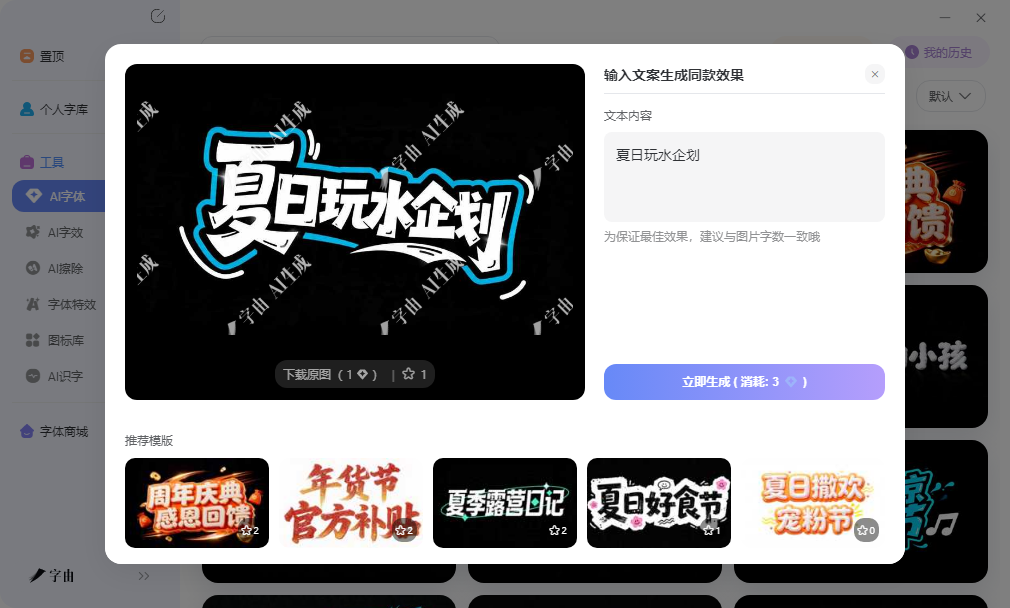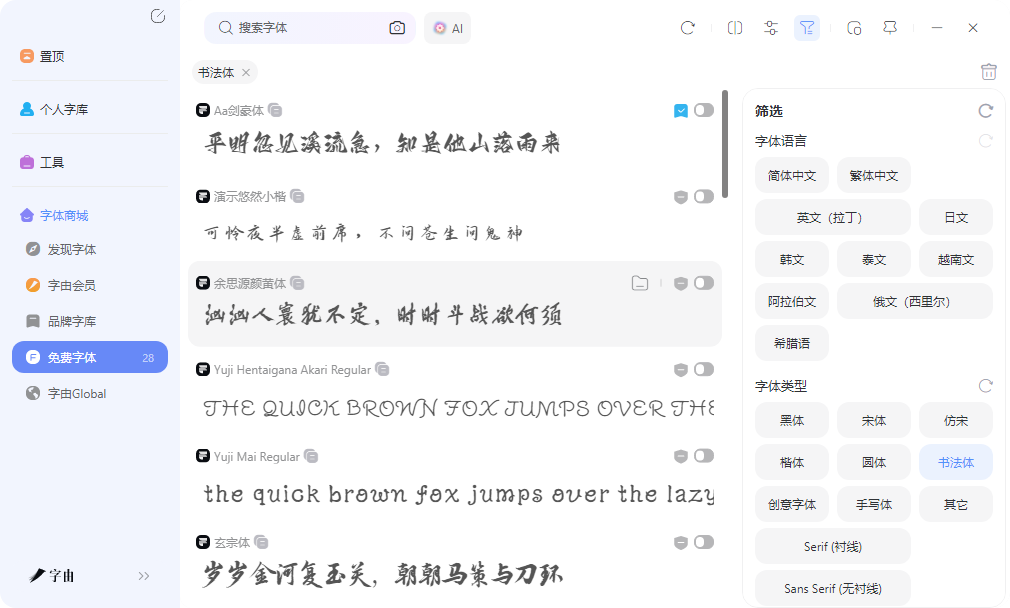
做中式海报缺书法字?这5个在线生成器30秒出毛笔效果
做中式海报或者文创包装时,书法字往往是视觉焦点。但书法字体文件通常比普通中文字体大很多。而且平时写正文、做商务PPT根本用不到书法体,只有春节海报、文创包装、中式品牌物料这类特定项目才需要,装完用一次就闲置在硬盘里。现在有不少书法字体在线生成工具可以直接出图,输入文案就能拿到带毛笔效果的PNG素材,不需要安装字体文件,生成好了直接可以用。
字由处理书法体需求的方式比较实用,因为中文字体本身字符集就大,书法体为了保留笔锋细节,字形数据更复杂,一个完整字符集的书法字体文件可能达到十几兆甚至几十兆。对于只需要做一张海报标题的设计师来说,下载安装这么大的文件,用完之后长期占用硬盘空间,性价比不高。
字由的AI字体功能提供了一种替代方案。模板库里有不少书法风格的特效模板,各种方向都有覆盖。输入自己的文案,比如品牌标语或者活动主题,大约二十多秒后生成一张透明背景的PNG图片。这张图片可以直接拖进海报或者电商详情页里做标题,不需要安装字体文件,也不需要担心系统字体列表臃肿。项目结束素材留在设计稿里,不会在硬盘里留着一个几十兆的字体文件长期吃灰。
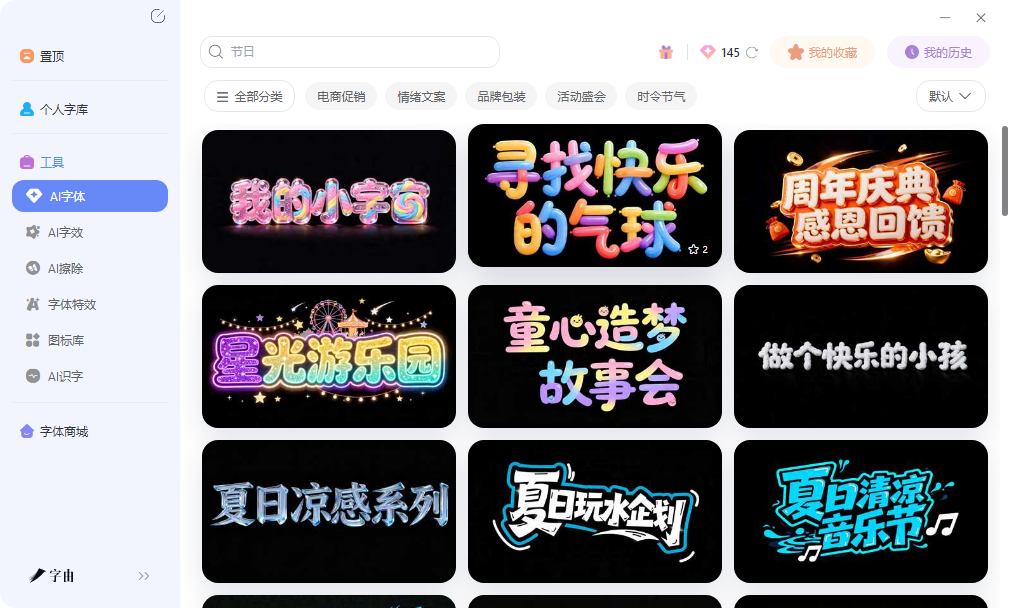
字由字体库里也有不少传统书法体,行书、楷书、隶书、草书在书法体分类下都有覆盖。和手写体不同,书法体偏向传统书体的数字化再现。预览框支持输入自己的文案,调整到实际使用字号后查看效果,确认清晰度再激活。激活后字体直接出现在设计软件里,不需要重启程序。对于需要长期使用某款书法体、而不是临时生成几张图片的用户来说,字体库里的资源可以激活后反复使用。
2、自由字体
自由字体是一个专注免费商用中文字体的平台,目前收录了近400款免费商用字体,其中包括不少书法体资源。网站上的书法体按风格做了分类,行书、楷书、隶书等类型都有覆盖,每款字体都标注了授权信息。
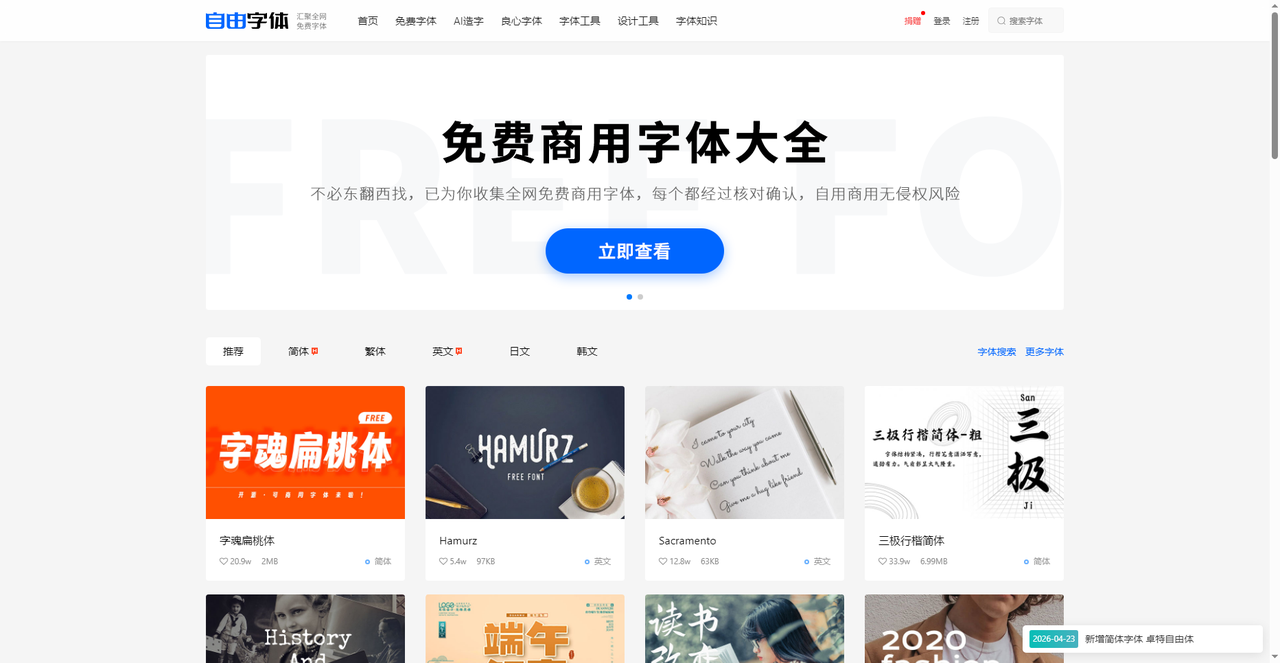
3、找字体网
找字体网主要是一个字体识别和下载平台,但也提供了在线字体生成功能。输入文字后,可以选择不同的字体风格进行预览和生成,其中包括部分书法体风格。
作为书法字体在线生成的辅助渠道,找字体网的优势在于字体识别功能。看到一张海报或者图片上的书法字体效果很好,但不知道名称,可以上传图片进行识别。识别结果会匹配到平台上最接近的字体,如果该字体支持在线生成,可以直接输入自己的文案生成同款效果。这种从识别到生成的衔接比较实用,省去了凭感觉搜索再逐个确认的麻烦。
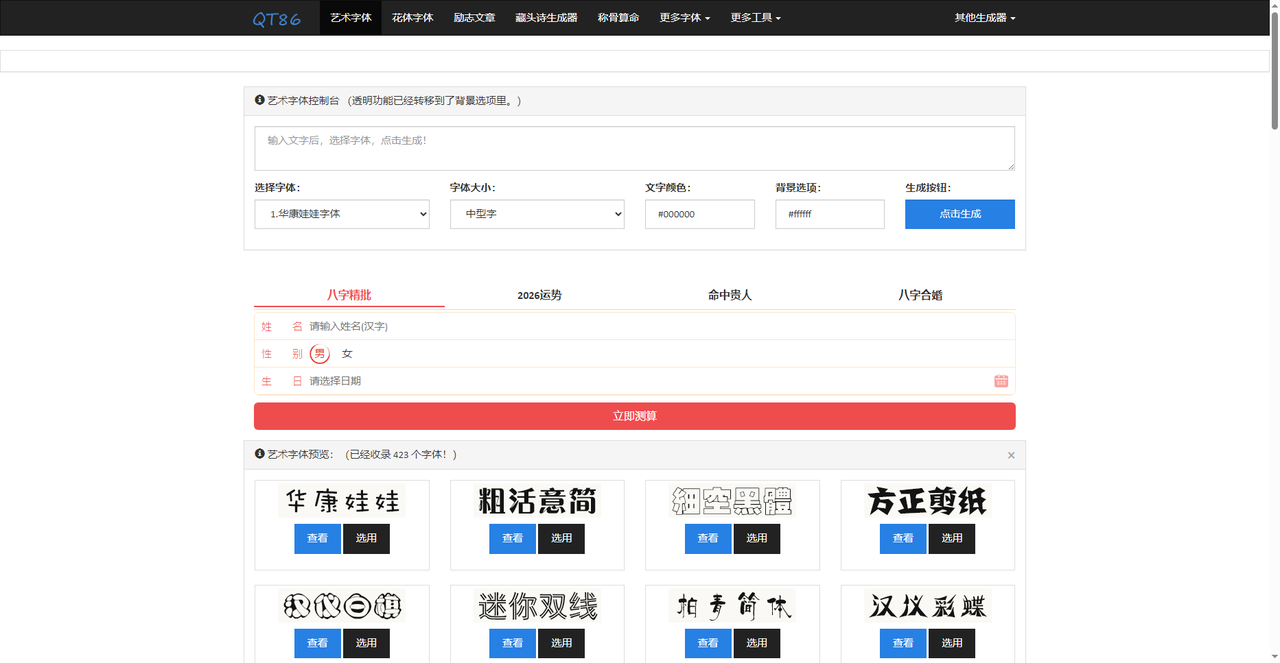
4、艺术字网
艺术字网是一个在线艺术字和书法字转换平台。输入文字后,系统会转换为多种艺术字体样式,其中包括不少书法风格。网站上的书法风格偏向装饰化处理,有些模板在传统书体基础上增加了现代设计元素,比如立体效果、金属质感、霓虹发光等。
作为书法字体在线生成的渠道,艺术字网的优势在于风格多样化,既有传统书法韵味,又有现代创意变体。对于想做中式风格但又不希望过于古典的项目来说,这里的创意书法风格比较匹配。生成的图片可以直接下载,流程简洁。网站上还提供了多种预设模板,点击即可切换,不需要手动调参数。
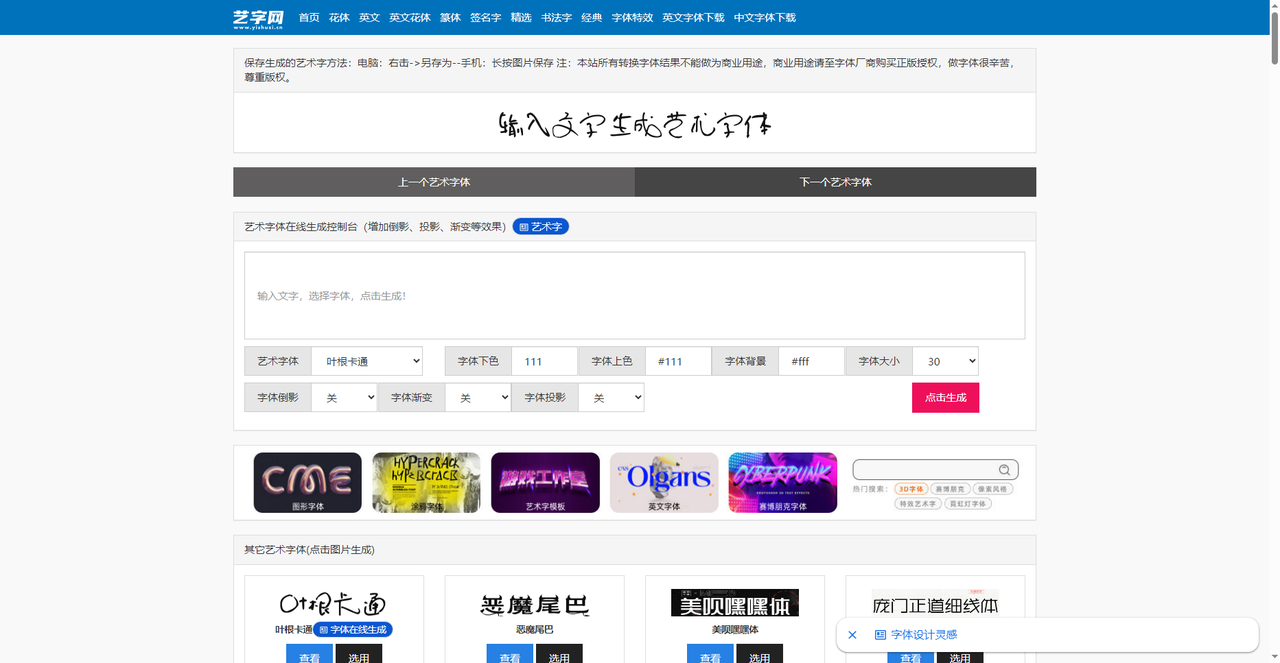
5、阿酷字体
阿酷字体是一个在线艺术字生成平台,支持多种书法风格转换。输入文字后,可以选择行书、楷书、隶书、草书等多种书体风格,系统会生成对应的书法字图片。网站上还提供了多种特效选项,比如描边、阴影、渐变等,可以进一步美化生成的书法字。
作为书法字体在线生成的渠道,阿酷字体的优势在于书体分类比较传统,覆盖了主流书法类型。生成的图片可以直接下载使用,也可以复制到剪贴板粘贴到其他地方。对于需要快速获得正统书法效果、且不需要安装字体文件的用户来说,这里的操作流程比较顺畅。网站还支持调整字号和颜色,可以微调效果以匹配具体需求。
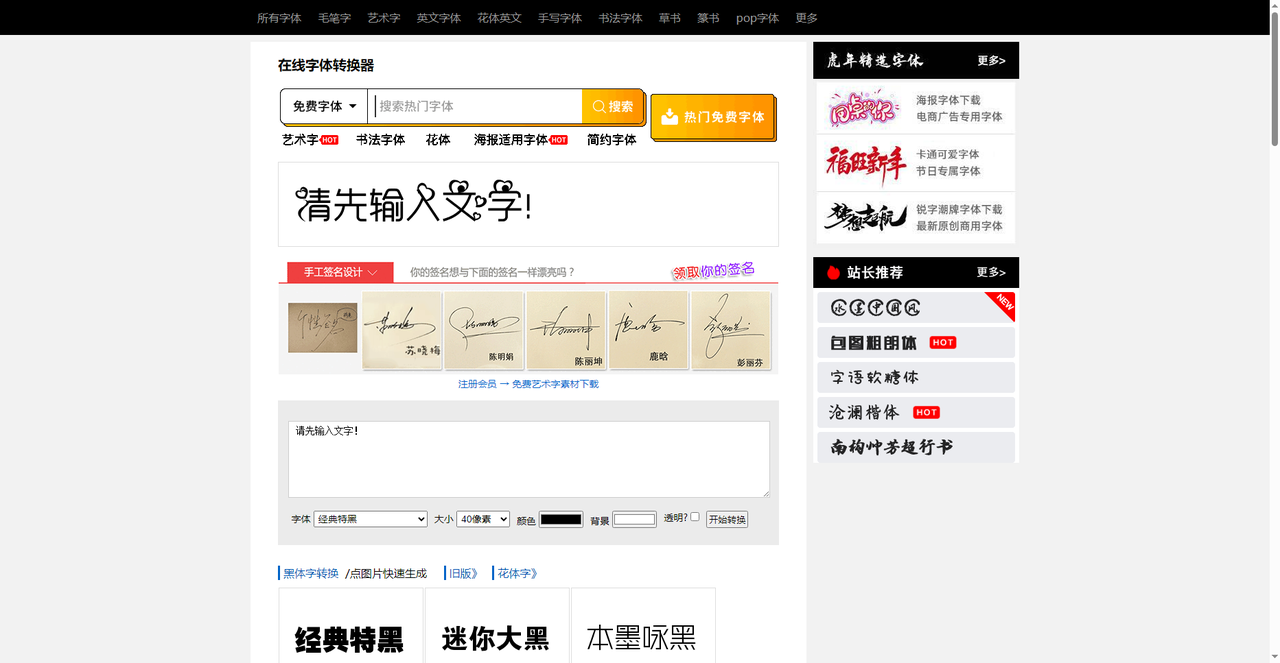
做中式海报或者文创包装,书法字体的获取方式取决于使用频率和项目需求。偶尔需要做几张标题图,字由的AI字体生成透明背景PNG,不用安装大体积字体文件,配合每日免费额度成本比较可控,作为书法字体在线生成的主力渠道比较实用。阿酷字体适合快速获得正统书法效果。艺术字网的创意变体适合现代中式风格。找字体网的识别功能对补充未知书法字体比较实用。自由字体则是需要安装文件、长期储备书法体资源时的稳妥选择。